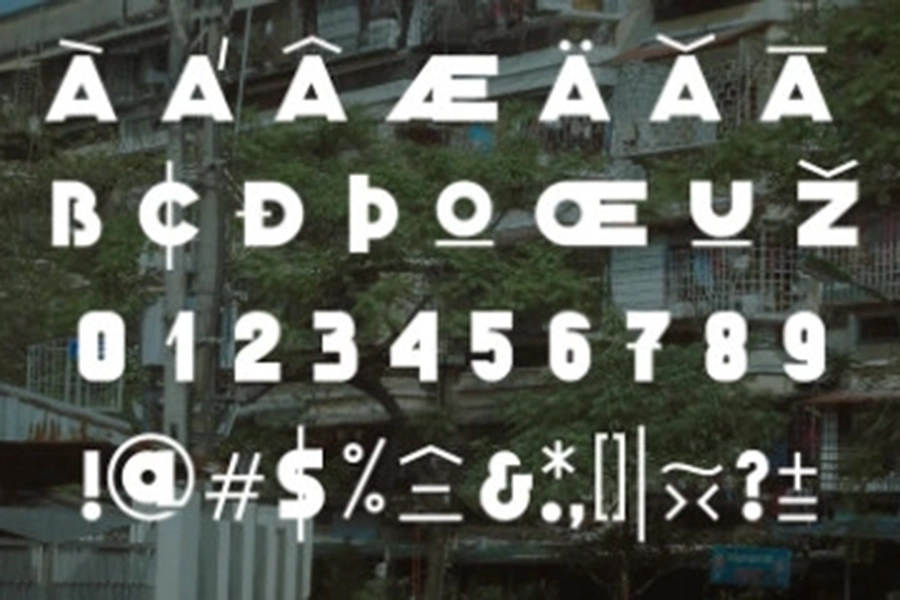
Classique Saigon mang đến cho người đọc cảm giác thư hoài niệm, lấy cảm hứng từ những câu khẩu hiệu, bài báo và các tác phẩm xưa cũ của Sài Gòn. Khi bạn muốn tải font chữ cho Photoshop việt hóa, Classique Saigon cũng là một lựa chọn tuyệt vời. Classique Saigon với Kiểu dáng nhẹ nhàng nhưng đầy phong cách các đường nét đơn giản nhưng tinh tế phù hợp với các ấn phẩm quảng cáo và in ấn mang phong cách vintage hoặc cổ điển.
Khi làm việc với Photoshop, lựa chọn font chữ không chỉ là chọn những đường nét đẹp mà còn phải phù hợp với ý đồ thiết kế tổng thể. Classique Saigon có nhiều ưu điểm khiến nó trở thành sự lựa chọn tuyệt vời cho các dự án thiết kế trên Photoshop:
Phong cách cổ điển đậm chất Việt Nam: Font chữ mang nét đẹp của thời kỳ xưa, phù hợp với các dự án mang hơi hướng truyền thống hoặc lịch sử.
Dễ đọc: Một trong những yếu tố quan trọng của font là khả năng đọc rõ ràng. Với Classique Saigon, người xem sẽ dễ dàng nhận diện và hiểu được nội dung mà bạn muốn truyền tải.
Tính thẩm mỹ cao: Kiểu dáng tinh tế, cân đối giữa các đường nét giúp font chữ này tạo ra những thiết kế đẹp mắt và thu hút.
Font Classique Saigon mà Hubservices vừa chia sẻ là sự kết hợp hoàn hảo giữa phong cách cổ điển và hiện đại, mang đến vẻ đẹp thanh lịch và tinh tế cho các dự án thiết kế trên Photoshop. Khi sử dụng font này, bạn không chỉ có thể tạo ra những sản phẩm ấn tượng mà còn giúp tối ưu hóa hiệu quả truyền tải thông điệp. Hãy thử nghiệm Classique Saigon trong các dự án của bạn để thấy được sự khác biệt!